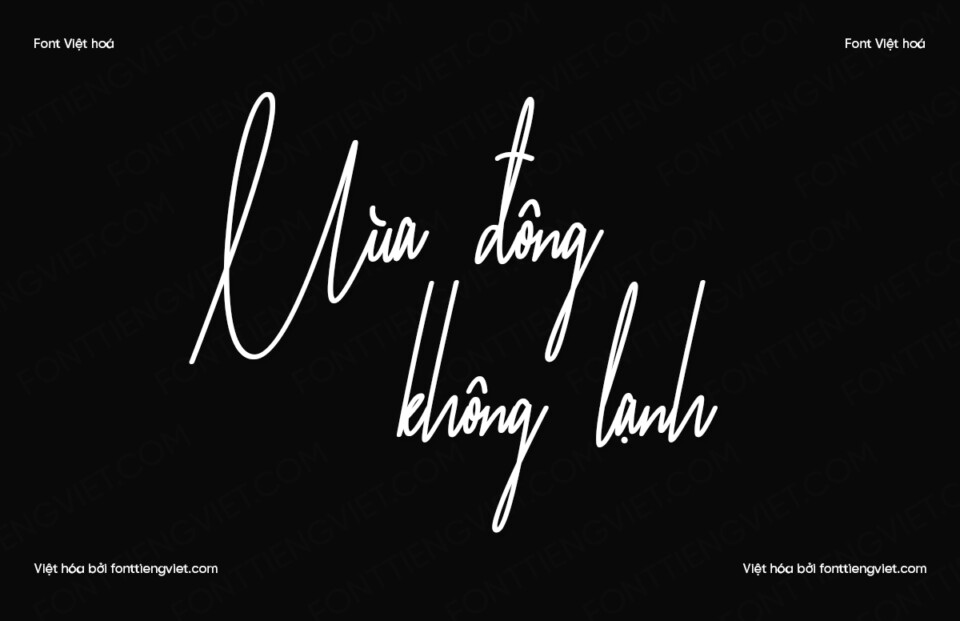
Giới thiệu về Font Việt hóa 1FTV VIP Maltoray Slant
Trong thế giới đồ họa hiện đại, việc tìm kiếm một bộ Font Chữ vừa mang nét cổ điển vừa giữ được sự năng động là điều không hề dễ dàng. Font Việt hóa 1FTV VIP Maltoray Slant xuất hiện như một giải pháp hoàn hảo dành cho những ai yêu thích phong cách Script mạnh mẽ và nghiêng một góc tinh tế. Đây là phiên bản được tinh chỉnh kỹ lưỡng, hỗ trợ đầy đủ tiếng Việt để người dùng thoải mái sáng tạo mà không lo lỗi ký tự hay khoảng cách. Với cấu trúc nét chữ thanh thoát nhưng đầy nội lực, bộ font này thường xuyên được các nhà thiết kế tin dùng cho các dự án mang tính biểu tượng cao.
Đặc điểm nổi bật của Font Việt hóa 1FTV VIP Maltoray Slant
Phong cách thiết kế độc đáo và hiện đại
Đặc trưng lớn nhất của Font Việt hóa 1FTV VIP Maltoray Slant chính là độ nghiêng (slant) đặc trưng tạo cảm giác tốc độ và sự chuyển động không ngừng. Các đường nét được bo tròn mềm mại ở những điểm nối nhưng lại sắc sảo ở phần kết thúc, giúp văn bản trở nên cuốn hút hơn. Kiểu chữ này cực kỳ phù hợp cho việc thiết kế logo, áo thun, hoặc các ấn phẩm quảng cáo cho ngành thể thao và xe máy. Sự kết hợp giữa tính nghệ thuật và ứng dụng thực tiễn khiến nó trở thành một lựa chọn VIP trong cộng đồng thiết kế tại Việt Nam.
Khả năng ứng dụng đa dạng trong thực tế
Dù bạn là một học sinh đang làm slide thuyết trình hay là một chuyên gia marketing chuyên nghiệp, bộ font này đều đáp ứng tốt mọi yêu cầu. Nó hoạt động mượt mà trên các phần mềm phổ biến như Adobe Photoshop, Illustrator hay ngay cả các ứng dụng văn phòng cơ bản. Nhờ sự tối ưu hóa về hiển thị, chữ viết luôn rõ ràng ở cả kích thước lớn lẫn nhỏ.
Kết luận và trải nghiệm sử dụng